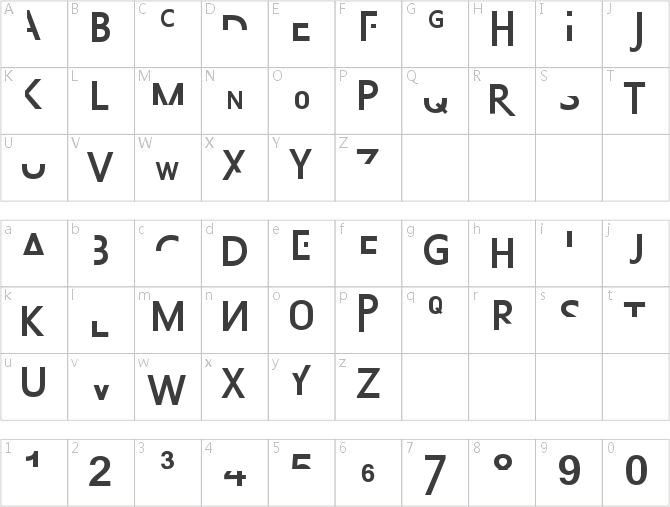
Absurdsans FP 詳情頁(yè)
Absurdsans FP字體字庫(kù)是一款讓人賞心悅目、百看不厭的英文字體,適合各類廣告和產(chǎn)品包裝設(shè)計(jì)應(yīng)用,字體大小0.03MB,格式為ttf字體,上傳用戶是東方時(shí)尚,作者/版權(quán)方為未知